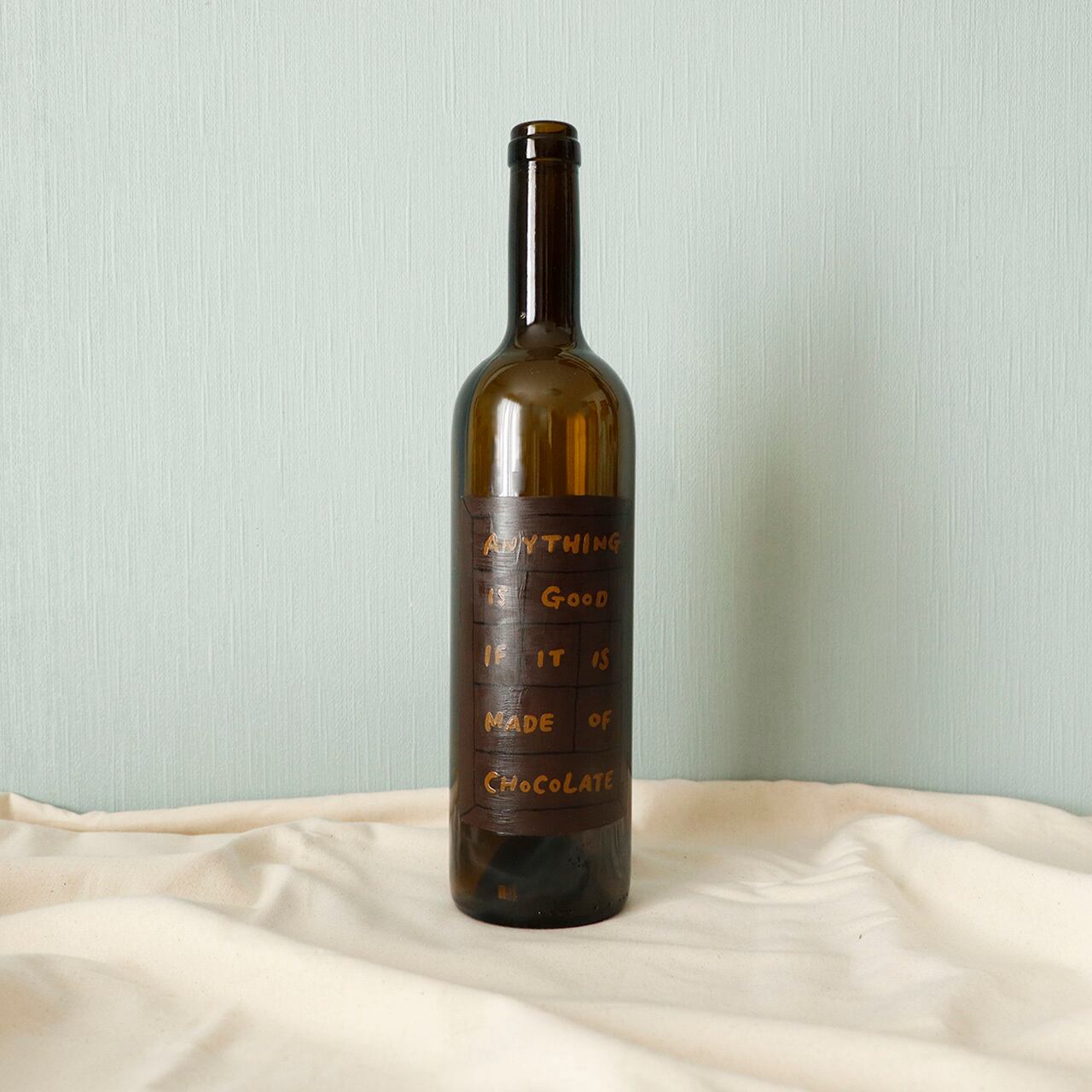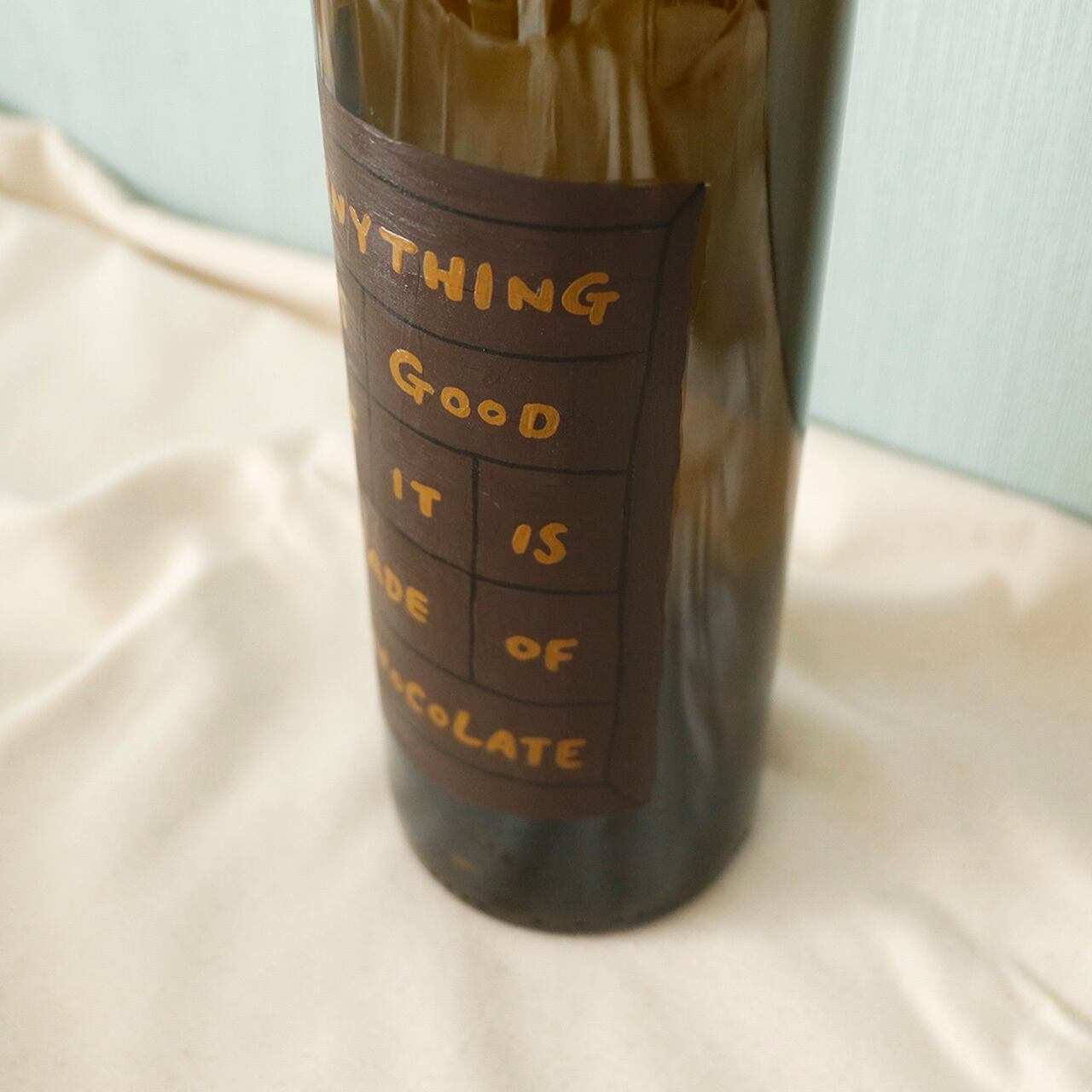
【BOTTLE PAINT ART】Anything is good if it’s made of chocolate.
Anything is good if it’s made of chocolate.
それがチョコレートで出来ているのならば、何だって美味しい。
チョコレート好きにはたまらない言葉!
ラベル風ですが、よく見ると板チョコになってます。
光が入るとこに置くと、瓶の色とともに文字も影になって素敵ですよ!!